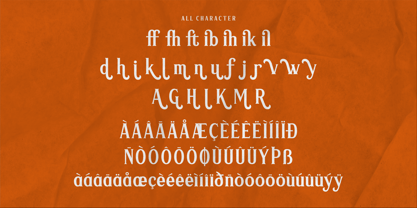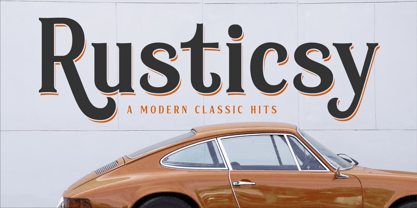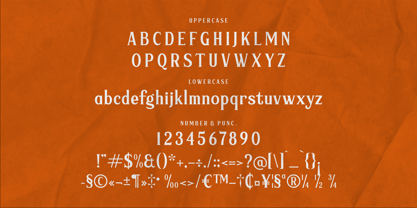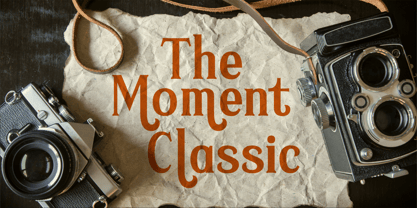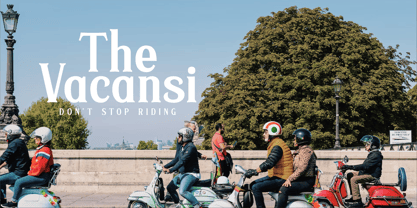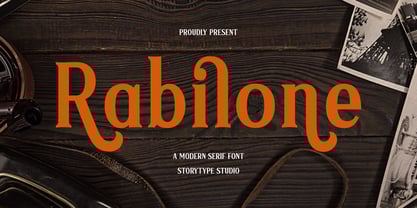
Rabilone
La familia tipográfica Rabilone fue diseñada por Heru Utama Putra y publicada por Letterena Studios. Rabilone contiene 2 estilos y opciones de paquete familiar.
Rabilone is a modern and stylish serif font that has its own unique appearance. This typeface is perfect for an elegant and luxurious logo, fashion brands, magazines, apparel, lettering, quotes, and so much more.